Was nicht in die Noten passt, wird als Notiz angefügt: Anweisungen für den Vortrag, Stimmungsangaben, kleine Erklärungen für den Spieler. Die moderne Notenschrift ist eine Hochsprache der Musik — präzise, dicht, fast übergenau. Sie erlaubt einer Komponistin, ein Werk so aufzuschreiben, dass es ein Orchester am anderen Ende der Welt im Wesentlichen identisch aufführen kann.
Moderne Noten
In der modernen Notation ist nahezu alles festgelegt: Notenschlüssel, Tonart, Taktart, Dynamik, Tempo, Halte- und Bindebögen, n-Olen, Tremolonoten und sogar Hinweise für einzelne Instrumente — vom Pedalzeichen für Klavier bis zum Flageolett für Streicher.
19.–21. Jahrhundert
Musik, in jeder Faser festgehalten
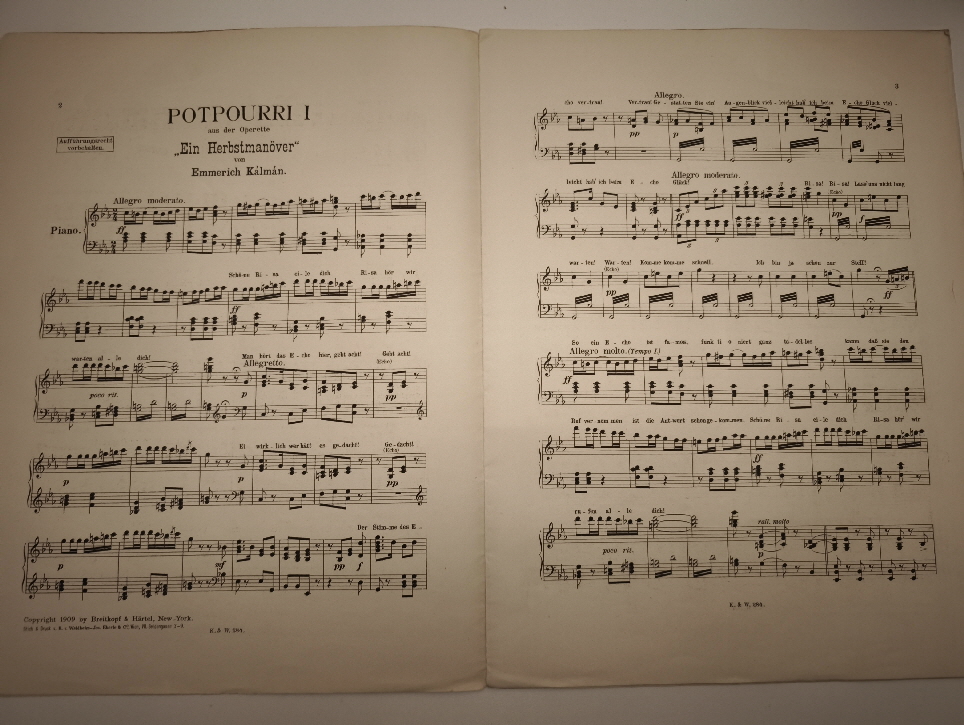
Emmerich Kálmán
Partitur einer Operette
Eine Seite aus einem Werk Emmerich Kálmáns zeigt, wie viel Information in moderne Notenschrift gepackt wird: mehrere Stimmen übereinander, Tempo- und Vortragsangaben, Dynamikgabeln, Phrasierungsbögen. Die Partitur ist Bauplan und Drehbuch zugleich.